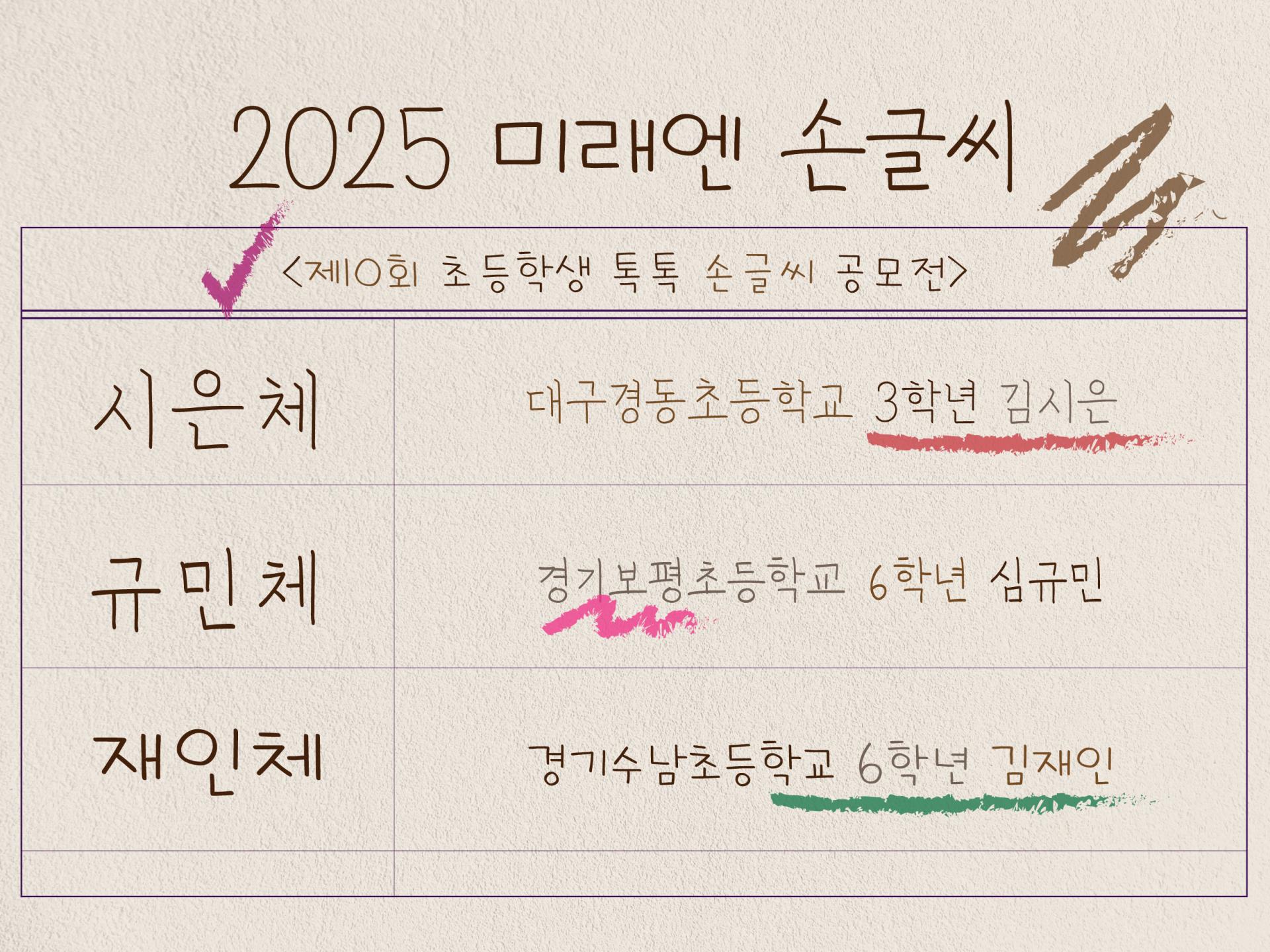
미래엔 [2025 손글씨공모전]
미래엔에서 개최한 2025년도 ‘제 10회 손글씨 공모전’에서 수상한 학생들의 이름으로 서체를 개발하였습니다.
폰트 6종 / 한글 2,350자 / 영문 94자 / 특수문자 986자
김시은, 심규민, 김재인
[미래엔 손글씨 공모전 서체]는